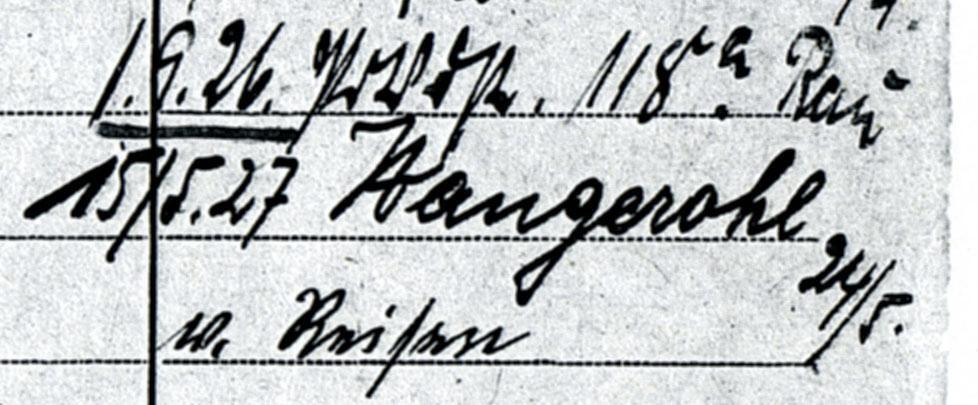
Mysteriöser Ortsname in alter Meldekarte aus Berlin
zuerst ein freundliches "Guten Tag" an alle in diesem Portal, das ich per Internet-Suche gefunden habe. Durch die Sachkunde der Teilnehmer hier scheint mir der Versuch vielversprechend, also probiere ich es einfach mal... Ich habe ein Rätsel von einer alten Meldekarte aus Berlin. Die Geschichte ist durchaus ironisch... nahezu alle 4 Millionen Meldekarten aus Berlin wurden zwar "gerettet", wurden dann aber nach dem Krieg aus unbekannten Gründen vernichtet und sind heute komplett verloren. Nur eine sehr kleine Zahl blieb erhalten.
Ich erforsche privat seit ein paar Jahren (für ihre Familie) das Leben einer Künstlerin, die 1927 aus Berlin für einige Jahre "verschwand" und für diesen Zeitraum bislang unauffindbar blieb, bis sie einige Jahre später nach Berlin zurückkehrte. Wie durch ein Wunder ist ihre Meldekarte eine der wenigen überhaupt, die heute noch existieren - und jetzt kommt die Ironie: Das wichtigste Wort darauf hat sich bislang als unlesbar bzw. unverständlich herausgestellt...
Es geht um diese Zeile:
Die Spalte benennt die Orte/Städte/Adressen, zu denen die Person weggezogen ist, und eigentlich scheint das Wort sogar ganz gut lesbar zu sein, es sieht aus wie "Hangerohl". Das Problem: Es gibt keinen auffindbaren Ort mit diesem Namen.
Ich habe natürlich als Erstes dort nachgefragt, wo die größte Kompetenz mit solchen Fragen zu finden ist, nämlich im Archiv in Berlin, und dazu auch noch bei Mitarbeitern im Hamburger Stadtarchiv, da es damals familiäre Verbindungen in diese Region gab. Die Mitarbeiterinnen und Mitarbeiter in diesen Archiven (und auch noch einem dritten hier vor Ort) waren alle sehr motiviert, bei diesem Rätsel zu helfen, und fragten auch jeweils im gesamten Kollegenkreis nach. Es gab einige Vorschläge:
- Das "H" könnte auch eine "St"-Ligatur sein, nur gibt es "Stangerohl" auch nicht.
- Als mögliche Alternativen wurden noch "Poerngerohl" oder "Poemgerohl" vorgeschlagen, aber auch die gibt es nicht.
Die Schrift sieht halt irgendwie durchaus sorgfältig aus, aber ich weiß aus eigener Erfahrung, wie schnell sich bei häufiger Handschrift eine Sauklaue entwickeln kann... mein "u" und mein "n" sind faktisch der gleiche Schnörkel.
Ich sehe nun zwei Möglichkeiten:
1) Einer der Buchstaben ist (durch permanentes Schreiben) zu einer anderen Form degeneriert. Hat jemand eine Idee, welche andere Schreibweise man hier noch herauslesen könnte?
2) Es war ein phonetisches Mißverständnis. In diesem Fall hätte das Rätsel nichts mit Typografie und Schriften zu tun, aber falls jemand zufällig einen lokalen Ort kennt, den man (phonetisch ausgesprochen) mit dem Wort "Hangerohl" oder so ähnlich verwechseln könnte, wäre ich für einen Tip natürlich auch sehr dankbar.
Alle anderen Einträge auf der Karte (in ähnlichen Handschriften und von mehreren Personen) konnten wir sinnvoll entziffern und zuordnen, es ist dieses eine Wort, an dem nun alle weiteren möglichen Recherchen am bezeichneten Ort abhängen...
Die ganze Karte möchte ich nicht veröffentlichen, da es ja auch persönliche und private Daten sind und die Einträge (gesichert) für diese Zeile nicht relevant sind. Sie stammen von unterschiedlichen Beamten über einen Zeitraum von mehreren Jahrzehnten.
Der Strich über dem ersten Buchstaben "von oben" ist aber natürlich etwas irritierend, hier sind die drei Zeilen im Kontext:
Die obere Zeile lautet (gesichert) "Potsdamer Straße", der Name "Rau" daneben ist ebenfalls verifiziert. Die Zeile darunter lautet nach einstimmigen Urteil der befragten Archivare "auf Reisen" und wurde erst nach 1928 von einer anderen Person hinzugefügt.
Der kleine/kurze zweite Strich neben der Unterlänge von oben dürfte evtl. zum fraglichen Wort gehören.
Alle anderen Einträge darüber und darunter stammen von völlig anderen Personen aus anderen Zeiten und haben keinen Bezug zur fraglichen Zeit ab 1927.
die dritte Zeile würde ich lesen:
w.[egen?] Reiſen
…angerohl  ist eindeutig zu lesen. Nur: Tante Goggel findet für  angerohl  gar nichts.
Das ist wirklich mysteriös.
Unter der Prämisse, dass der Eintrag aufgrund einer mündlichen Angabe erfolgt ist und der Name mit St anfängt, gibt es in Österreich zwei Orte namens Stang, von denen mindestens einer ein Gewässer benamthttps://de.wikipedia.org/wiki/Stang_(Gemeinde_Kirchschlag)
Mit dieserlei unwissenden Mutmaßung* könnte ich mir einen Ort/Hof/wasauchimmer Stanger Aue plus einem Sack voller Mundarten vorstellen.
Aber dass aus diesem blinden Gerate etwas wird, bräuchten wir durchaus noch mehr Informationen zur Biographie etc.
*) Ich bin null kundig in Ahnenforschung, aber so wird ab und wann im Bereich der Antikenwissenschaften Orte als möglicherweise identifiziert.
Wie auch immer, wenn man nicht jede Spur verfolgt, braucht man gar nicht erst anfangen, und wer in Zukunft das hier zufällig liest und noch andere Ideen hat, wir sind für *jede* Theorie dankbar, egal wie absurd sie klingen mag. Wenn überhaupt eines Tages, dann wird dieses Rätsel auch nur durch einen Zufall gelöst werden können...